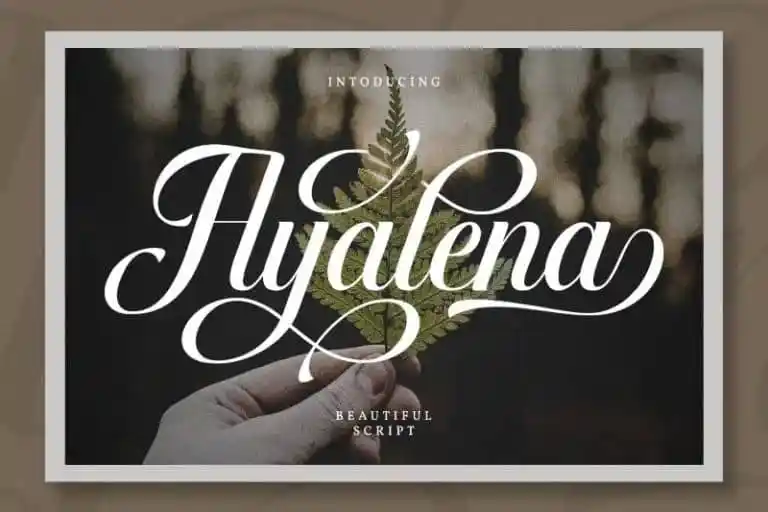
Ayalena Calligraphy Font – Download Grátis
Ayalena Calligraphy Font é uma fonte calligrafia moderna, criada pela Din Studio através de suas habilidades para trabalhos manuscritos. Com corte final e início, esta fonte atinge um equilíbrio perfeito entre o moderno e a elegância da escrita à mão livre. Ideal tanto para projetos profissionais quanto para branding, Ayalena Calligraphy oferece uma excelente experiência para logos, identidades de marca, casamentos e citações. Com seu design fresco e sofisticado, esta fonte é perfeita para qualquer projeto que busque um toque de elegância natural. Sem dúvida, ela se destaca como a escolha ideal para quem deseja dar vida às suas mensagens com estilo e criatividade. O download gratuito desta demo versão garante uma experiência satisfatória enquanto você decide sobre outras opções únicas disponíveis no catálogo da Din Studio. Essa fonte é perfeita tanto para uso pessoal quanto para projetos profissionais, o que a torna um investimento inteligente na sua coleção de recursos gráficos. Seja para criar os logos do seu próximo projeto de marketing ou personalizar suas mensagens em redes sociais, Ayalena Calligraphy é uma escolha sólida e segura. Para explorar mais opções únicas, visite o site da Din Studio onde encontrará um leque diversificado de produtos. Ao adquirir uma fonte através desta plataforma, você não apenas está comprando um recurso gráfico incrível mas também está apoiando o trabalho dedicado do designer e desenvolvedor. Uma compra que reflete não só sua habilidade para selecionar recursos de alta qualidade, mas também a importância da sustentabilidade no mercado digital atual.